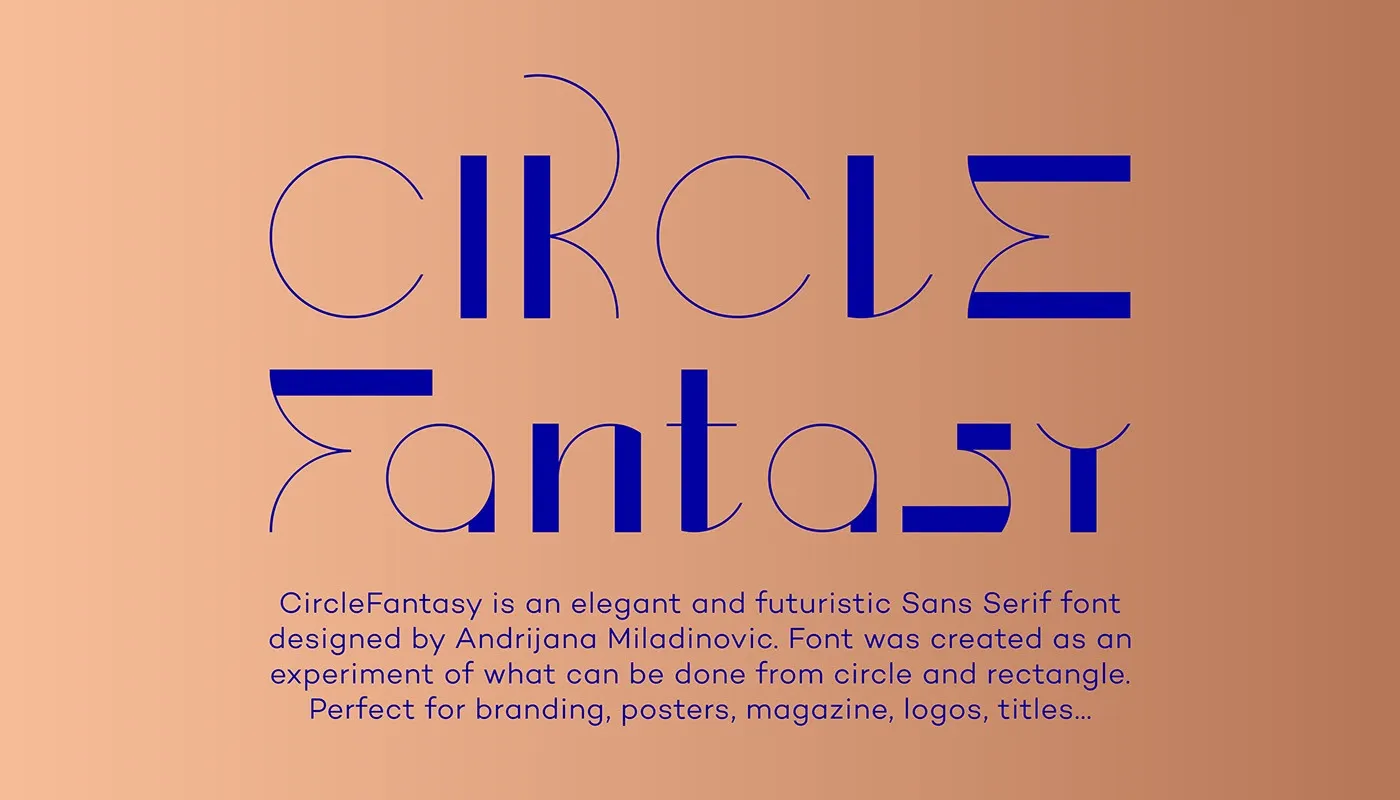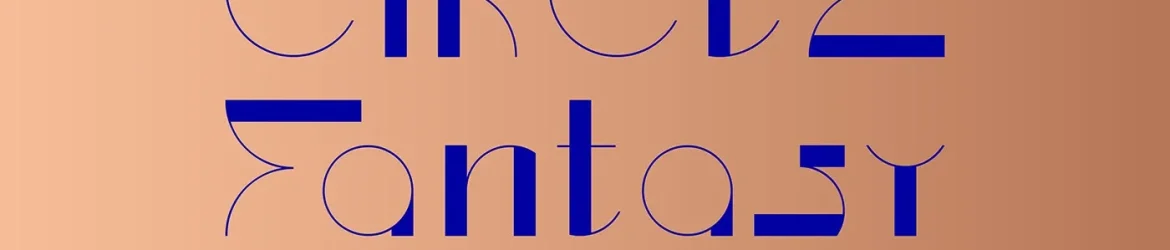
A fonte ‘CircleFantasy Font’ foi criada pela designer Andrijana Miladinovic para explorar as possibilidades que a geometria circular e retangular podem oferecer num tipo expositivo vintage e elegante. Desenvolvida como uma experimentação, esta nova fonte tem um uso óbvio em aplicações de marca, cartazes, revistas, logotipos e títulos. Suas formas arredondadas e linhas quadradas criam um contraste interessante que se assemelha a um desenho artístico moderno. Convidamos você para explorar uma fonte com características únicas, ideal para aqueles projetos que buscam dar um toque especial em qualquer tipo de material visual.